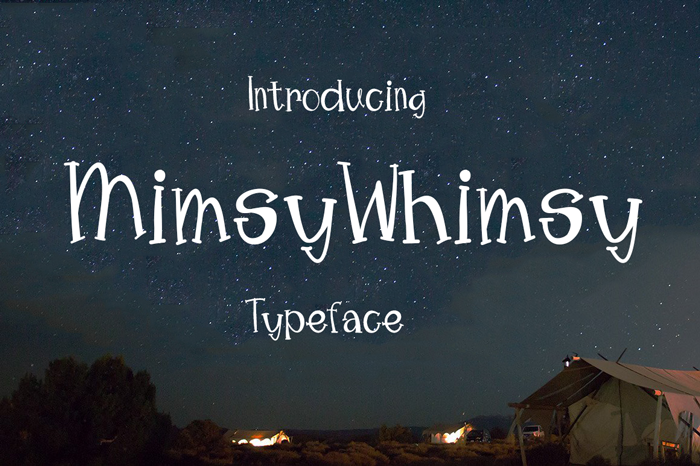
Mimsy Whimsy Typeface – Download Grátis
Aqui está uma descrição para a página de download da fonte “Mimsy Whimsy Typeface”, adaptada ao tom solicitado: Se você adora a leveza e criatividade do design visual, a “Mimsy Whimsy Typeface” é ideal para suas próximas criações. Este tipo de fonte tem um toque divertido que não só enriquece sua composição gráfica, mas também transmite um sentido inconfundível de leveza e energia aos seus projetos. Se você já apreciou a experimentação e criatividade desta fonte playfull, gostaríamos muito que considerasse fazer uma doação. Seu apoio financeiro é fundamental para permitir que continuemos dedicando tempo e esforço à nossa paixão pela criação de novas e divertidas fóntes. Sua contribuição fará uma grande diferença em nossos projetos futuros. Muito obrigado por sua consideração, e sem você, o nosso trabalho como designers não seria tão alegre nem diverso! Agradeçemos imensamente pelo seu interesse no nosso trabalho.